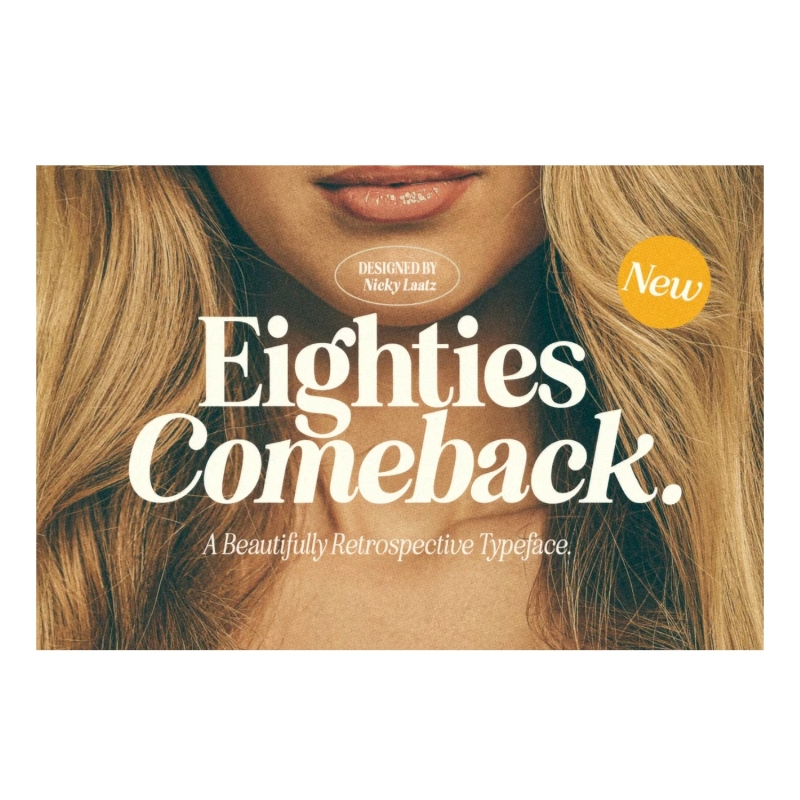
الثمانينات عودة Serif (70 خطوط)
• نمط النص: الرقيق
قل مرحبا ل "عودة الثمانينات" - محرف ساحر مستوحى من 80 مع تنوع رائع نظرا لأنه يتضمن 70 خطا. 2 يتم أيضا تضمين خطوط متغيرة مفيدة لأولئك الذين لديهم Adobe Photoshop / Illustrator CC 2020 وما فوق :)
مستوحاة من إعلانات المجلات من 70 و 80 - هذه العائلة تتناسب مع إعادة الرجعية إلى القرن 21st. متعدد الاستخدامات للغاية - قم بالتمرير عبر جميع المعاينات لرؤية مجموعة واسعة جدا من التنوع الذي يمكن أن تظهره Eighties Comeback ، فالاحتمالات لا حصر لها حقا :)